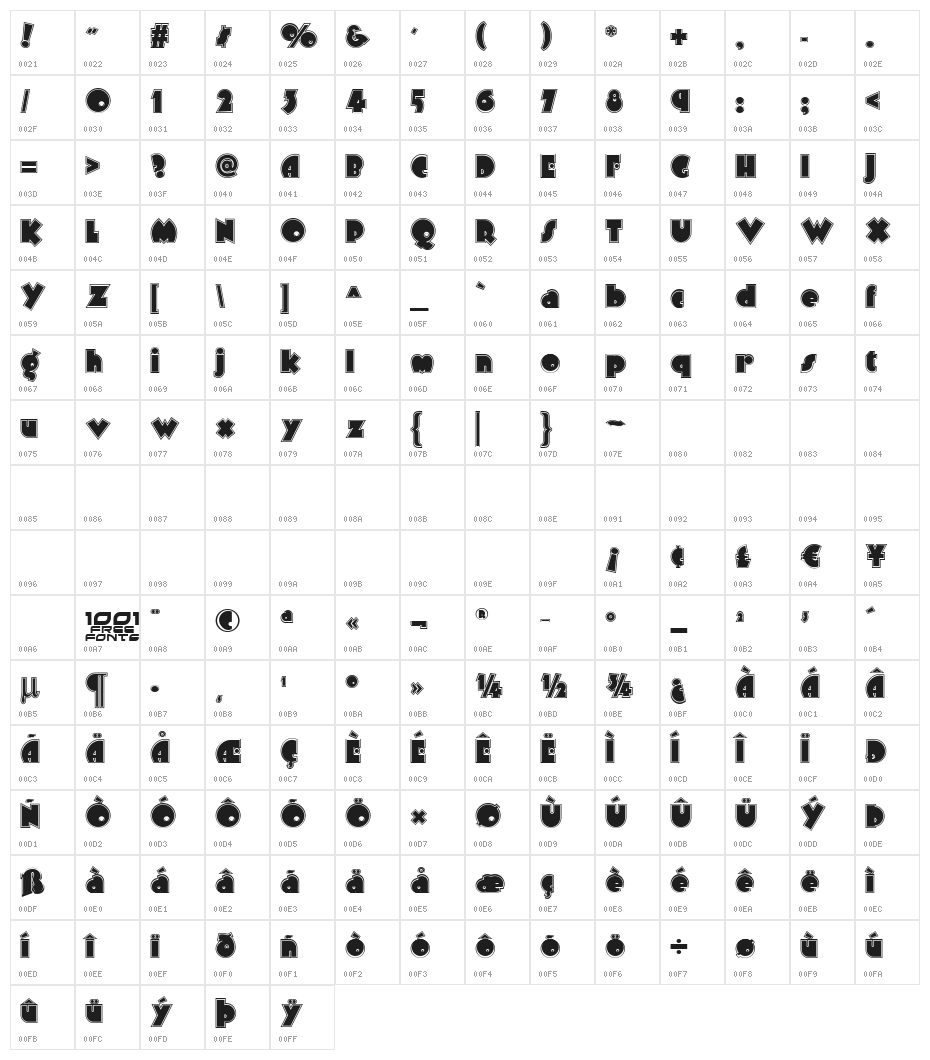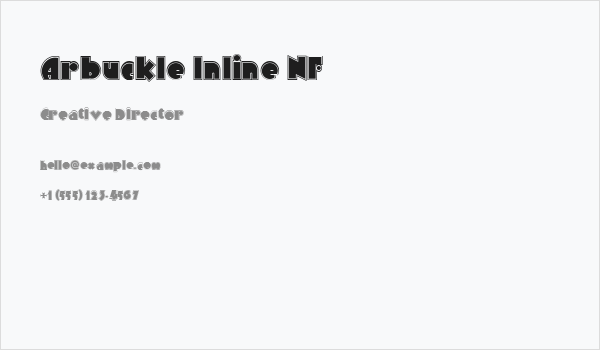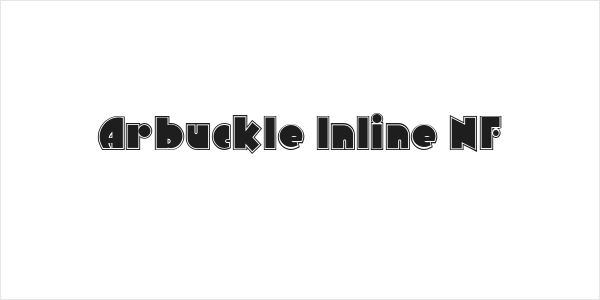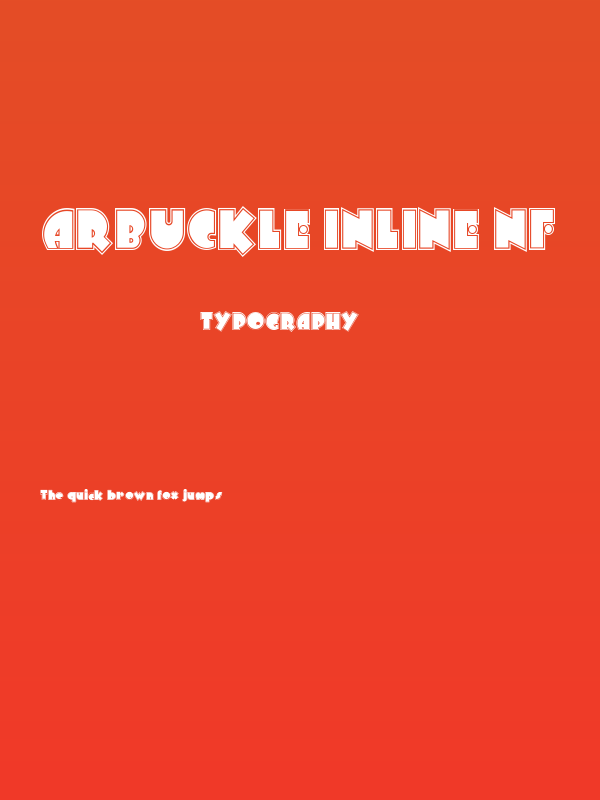
Arbuckle Inline NF Font
| Kategorien | Outline |
| Gesamtstil | Retro, Decorative |
| Vorgeschlagene Projekte | Ideal for posters, headlines, logos, and any design requiring a bold, retro aesthetic. |